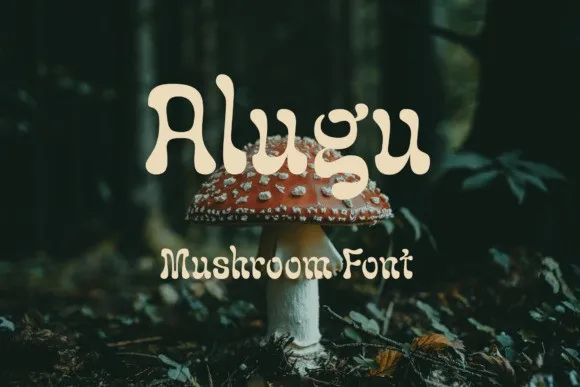
Esta é uma tipografia bold com toques retro que te levará ao ambiente 70s nostálgico. Foi criada pela YTY Digital TypeFoundry e compartilhada para você recapturar aquele clima despreocupado dos anos 1970. Alugu, fonte de categoria display, traz um toque inovador e único à sua produção. Perfeito para logotipos, identidades corporativas e muito mais, essa font será uma excelente adição ao seu portfólio. Completamente diferente e vibrante, ela é perfeita para levar seus trabalhos digitais a um novo nível de criatividade e estilo.